2023년 최고의 여성스러운 글꼴 21개(무료 및 프리미엄)
이 블로그 게시물에서는 디자인 작업을 향상시켜 줄 최고의 여성스러운 글꼴 21개 목록을 선별했습니다. 로고, 웹 사이트 또는 인쇄 프로젝트에서 작업하는 경우 이러한 글꼴을 사용하면 스타일리시하고 세련된 모양을 얻을 수 있습니다.
이제 왜 특별히 여성스러운 글꼴이 필요한지 궁금하실 것입니다. 글쎄, 연구에 따르면 특정 글꼴은 다른 감정을 불러일으키고 다른 메시지를 전달할 수 있습니다.
여성스러운 글꼴은 우아함, 섬세함 및 우아함으로 유명하므로 여성 청중을 대상으로 하거나 보다 부드러운 미학을 요구하는 프로젝트에 이상적입니다. 따라서 여성스러움이 필요한 프로젝트를 진행 중이라면 이 글꼴이 적합합니다.
그러나 우리의 말을 그대로 받아들이지 마십시오! 이 기사에서는 이러한 글꼴의 영향을 더 깊이 이해할 수 있도록 이러한 글꼴에 대한 몇 가지 흥미로운 통계와 사실을 제공합니다.
글꼴의 기원과 인기부터 다양한 산업에서의 사용에 이르기까지 이러한 글꼴이 많은 디자이너에게 선택받는 이유에 대한 귀중한 통찰력을 얻을 수 있습니다.
따라서 더 이상 고민하지 않고 여성스러운 글꼴의 세계로 뛰어들어 디자인을 다음 단계로 끌어올릴 수 있는 상위 21가지 옵션을 살펴보겠습니다. 당신이 노련한 디자이너이든 막 시작하든, 우리는 모두를 위한 무언가를 가지고 있습니다. 글꼴 탐색을 시작하자!
르보파
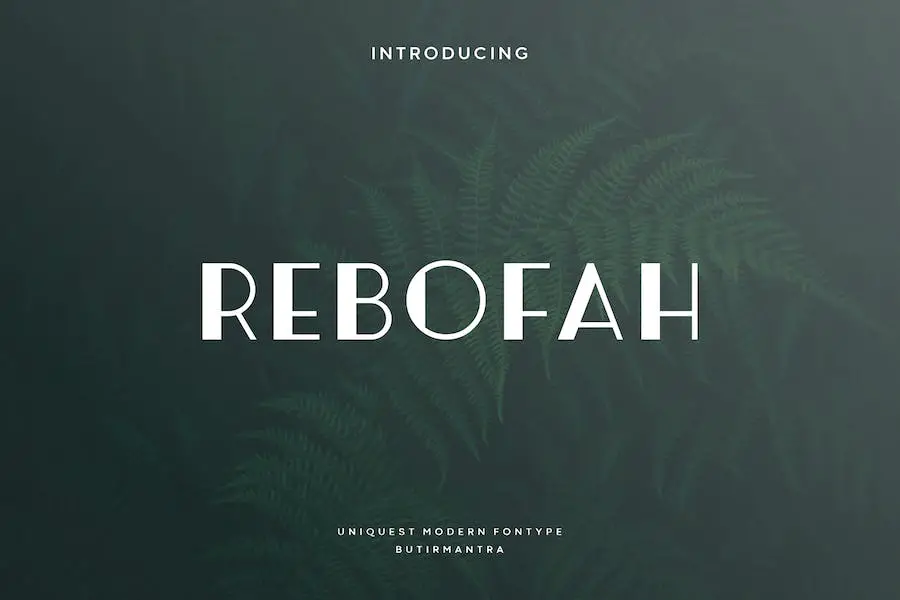
Rebofah는 독특한 스타일과 대문자에 약간의 트위스트를 제공하는 디스플레이 글꼴입니다. 음식, 일러스트레이션, 책 제목, 웹사이트 머리글, 비디오 작성 및 기타 그래픽 디자인 요구 사항과 관련된 프로젝트에 완벽한 선택입니다.
눈길을 끄는 모양과 다양한 기능을 갖춘 Rebofah는 디자인을 향상시키고 창의성을 더할 것입니다.
애니스톤
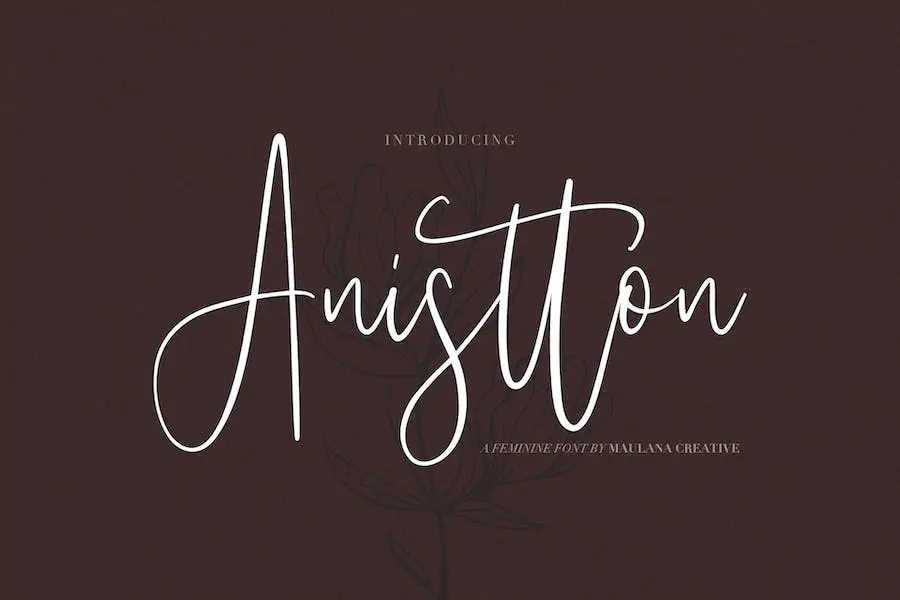
Anistton은 당신의 디자인에 정통 수공예 터치를 더해줄 글꼴입니다. 서명, 편지지, 로고, 타이포그래피 인용문 등에 적합합니다.
브러시와 같은 스타일로 잡지나 책 표지, 웹사이트 헤더, 전단지, 의류, 브랜딩, 패키징 등 다양한 디자인 프로젝트에 사용할 수 있는 다재다능한 애니스톤입니다.
소리녹 고우스
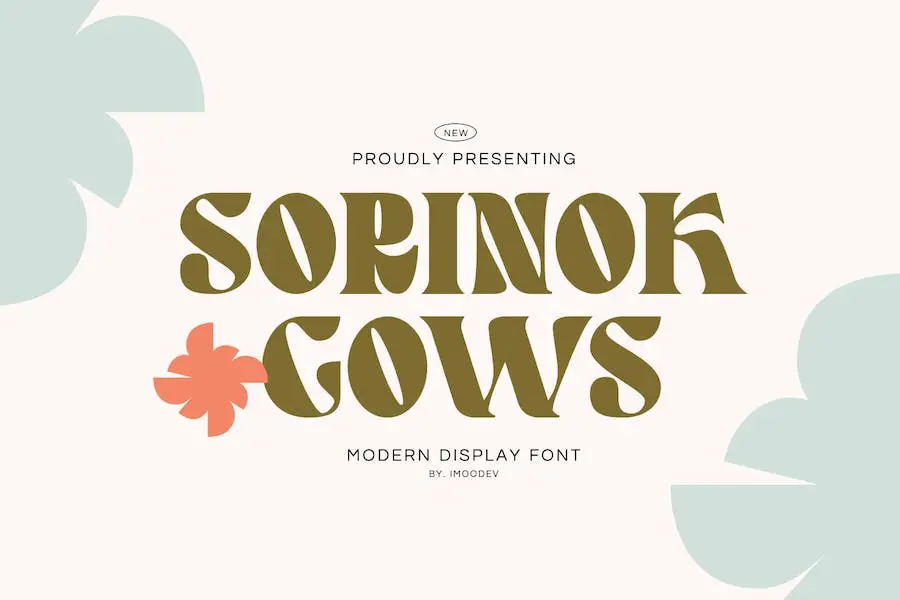
소리녹고우스는 크고 작은 사이즈 모두 사용이 가능한 다재다능한 폰트입니다. 개인 프로젝트부터 스튜디오, 기업체, 크리에이티브 에이전시, 산업체까지 다양한 비즈니스 분야에서 활용할 수 있습니다.
Opentype 기능과 다국어 지원을 통해 Sorinok Gows는 많은 유연성과 사용자 정의 옵션을 제공합니다. 구두점, 숫자, 기호, 대문자 및 소문자의 완전한 세트를 포함합니다.
스윗샤인
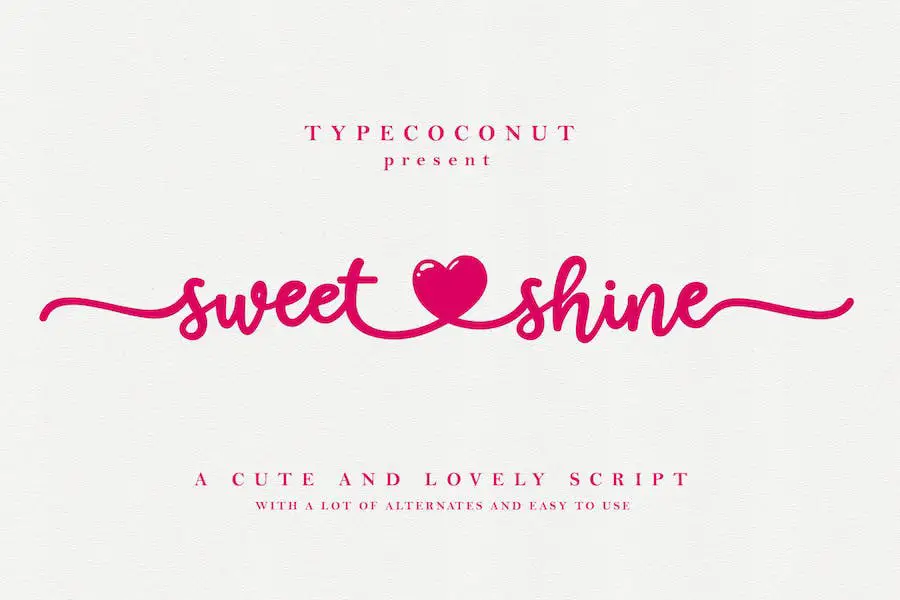
Sweet Shine은 다양한 프로젝트에 적합한 멋진 손글씨 스크립트 글꼴입니다. 공예 프로젝트, 웨딩 디자인 또는 현대적인 의류 작업을 하거나 눈길을 끄는 광고용 글꼴이 필요한 경우 이 글꼴이 이상적인 선택입니다.
아름답고 복잡한 레터링이 있는 Sweet Shine은 완벽한 구성을 만드는 데 도움이 되는 다양한 대체 스타일을 제공합니다. 손끝에서 개인 서예가를 갖는 것과 같습니다.
에사쿠
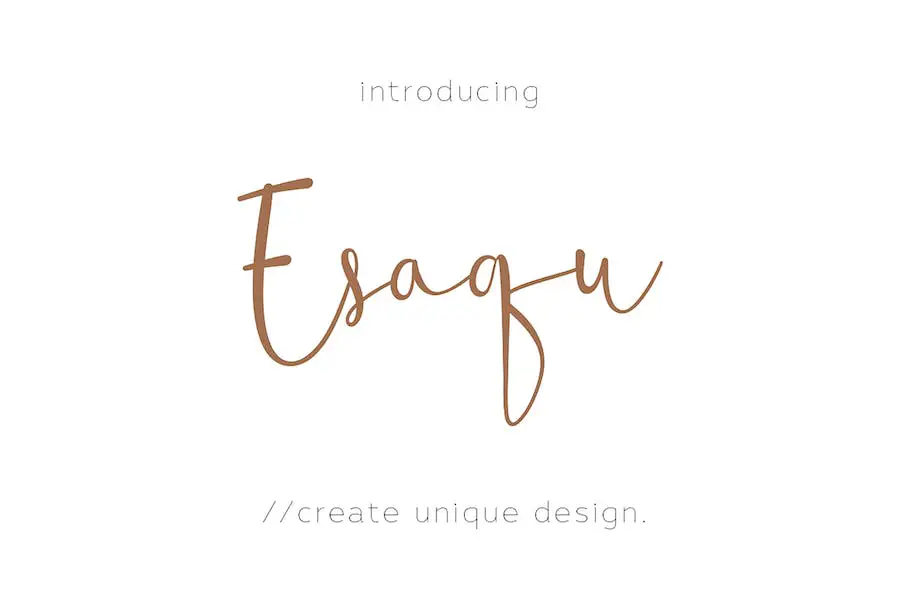
Esaqu는 디자인 프로젝트에 우아하고 독특한 터치를 더하는 세련되고 아름다운 여성스러운 글꼴입니다. 핸드 레터링 스타일로 어떤 디자인에도 자연스럽고 핸드메이드 느낌을 줍니다.
가느다란 선과 굵은 선의 조합과 깨끗한 스크래치가 어우러져 아름답고 시각적으로 매력적인 모습을 연출합니다.
브랜딩에 여성스러운 터치를 추가하고 싶거나, 멋진 청첩장을 만들거나, 눈길을 끄는 배너를 디자인하거나, 아름다운 로고와 레터링을 만들고 싶다면 Esaqu가 완벽한 선택입니다.
싱클레어
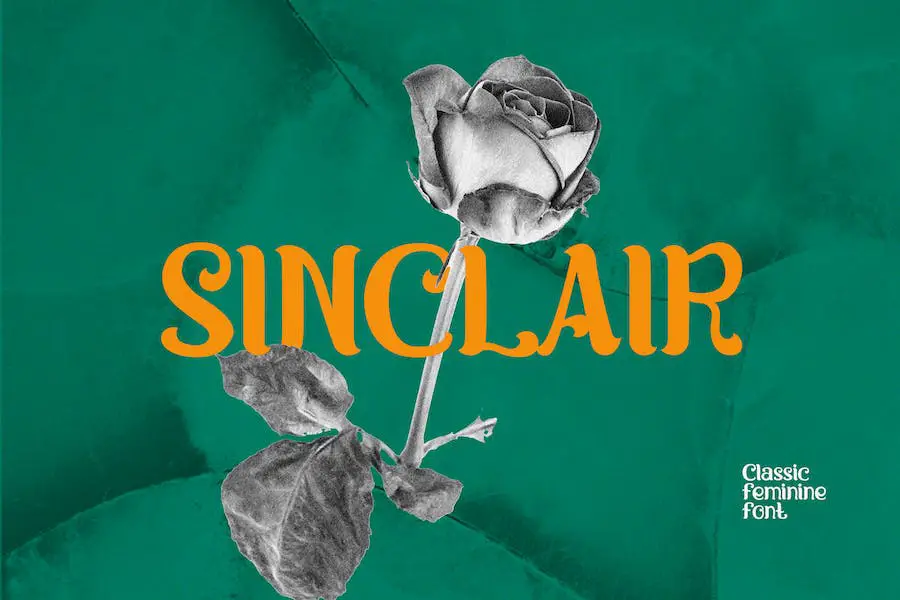
SINCLAIR는 모든 프로젝트에 화려한 스타일을 제공하는 우아한 여성스러운 느낌의 세리프 글꼴입니다. 세련되고 아름다운 디자인으로 디자인에 세련미를 더하는 데 적합합니다.
다양한 응용 분야에 적합한 SINCLAIR는 책, 여성스러운 포스터, 문구류, 학용품 글꼴, YouTube 표지, YouTube 섬네일, 소셜 미디어 페이지 표지 등에서 성숙하고 우아한 테마를 만드는 데 이상적인 다용도 글꼴입니다.
카말라
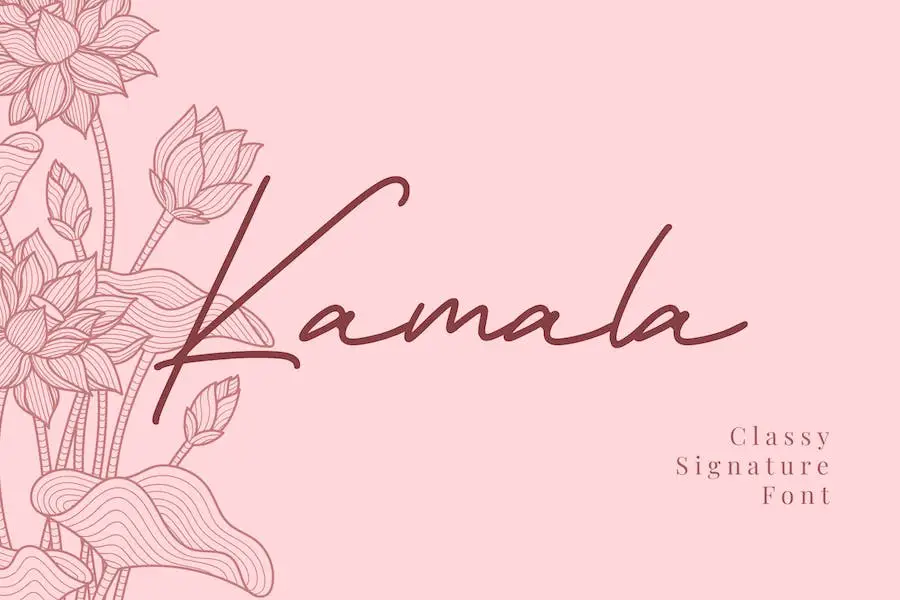
Kamala는 우아함과 다재다능함을 발산하는 시그니처 스크립트 글꼴입니다. 부드럽고 자연스러운 선이 있는 이 글꼴은 이름, 로고 또는 모든 디자인 프로젝트에 고급스러운 느낌을 더하는 데 적합합니다.
멋진 서명과 세련된 로고를 만들고 보석 및 유기농 식품 포장의 아름다움을 향상시키는 데 특히 이상적입니다. 또한 Kamala는 모든 로맨틱한 이벤트에 세련미를 더하기 때문에 청첩장을 위한 훌륭한 선택입니다.
안테미아
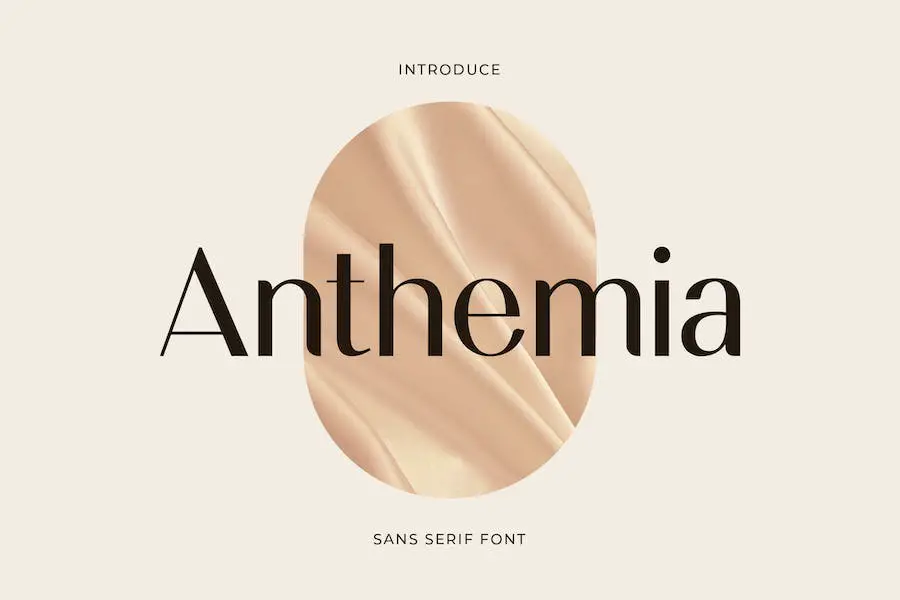
Anthemia는 프로젝트에 아름다움, 품격, 우아함을 더하기 위해 디자인된 멋진 여성스러운 세리프 글꼴입니다. 로고, 청첩장, 잡지 표지 또는 웹사이트 헤더 작업에 관계없이 이 글꼴은 모든 창의적인 노력에 완벽하게 적합합니다.
현대적이고 세련된 미학으로 다양한 스타일과 테마에 맞출 수 있을 만큼 다재다능합니다.
또한 여성적 특성과 남성적 특성을 자연스럽게 혼합하여 패션 관련 브랜딩 또는 편집 디자인에 탁월한 선택입니다. 귀하의 디자인에 우아함과 스타일을 더해줄 Anthemia만 있으면 됩니다.
뒤죽박죽 인
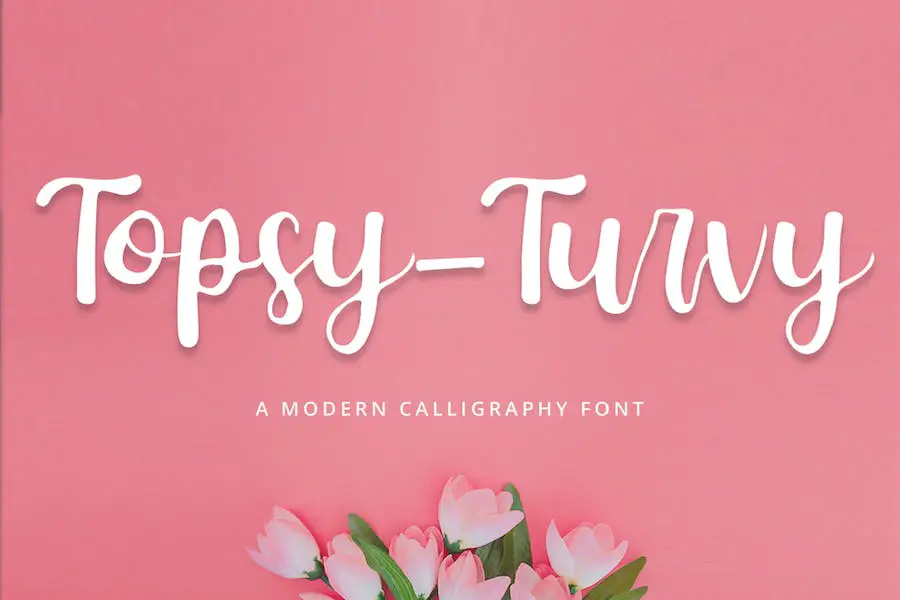
청중, 클라이언트 또는 손님을 사로잡을 재미있고 다양한 글꼴인 Topsy-Turvy를 소개합니다. 구두점과 숫자가 모두 포함된 이 현대적인 캘리그라피 글꼴은 프로젝트에 우아함을 더하는 데 적합합니다.
제목/제목과 본문 카피 사이에 완벽한 대조를 만들고 싶습니까? Topsy-Turvy가 답입니다. 뷰티 인플루언서, 인테리어 디자이너, 요리 유튜브 채널을 운영하는 등 다양한 콘텐츠 니즈와 프로젝트에 활용할 수 있는 폰트입니다.
사비아나
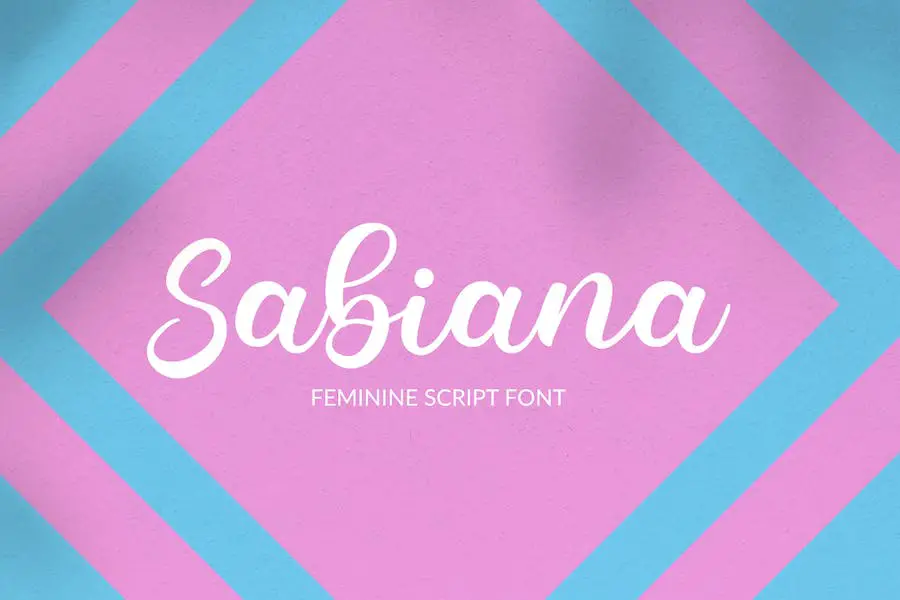
이 TTF 글꼴은 아름다운 브랜딩 프로젝트, 패셔너블한 잡지 레이아웃, 시선을 사로잡는 포장 디자인, 시선을 사로잡는 소셜 미디어 게시물을 만드는 데 적합합니다. 또한 청첩장 및 연하장을 위한 탁월한 선택입니다.
Sabiana의 뛰어난 기능 중 하나는 다양한 언어를 지원하여 광범위한 사용자가 액세스할 수 있다는 것입니다. 다른 언어로 디자인을 만들거나 국제 청중을 수용해야 하는 경우 이 글꼴을 사용할 수 있습니다.
발레인
Ballein의 눈에 띄는 기능 중 하나는 광범위한 대체 대문자 세트입니다. 즉, 선택할 수 있는 옵션이 매우 다양하여 프로젝트에 가장 적합한 것을 찾을 수 있습니다.
뿐만 아니라 Ballein은 합자를 여러 글꼴로 선택하여 훨씬 더 다재다능하고 창의적인 자유를 제공합니다.
가리
여성스러움을 더해 프로젝트를 향상시킬 수 있는 이상적인 글꼴을 찾고 있는 그래픽 디자이너라면 Girly가 적합합니다. 이 글꼴은 세련되고 매력적인 글꼴을 찾는 현대 디자이너의 요구를 충족시키기 위해 특별히 제작되었습니다.
우아하고 고급스러운 디자인으로 Girly는 시장에서 가장 좋아하는 제품이 될 것입니다. Girly의 주요 기능 중 하나는 다양성입니다.
이 세리프체는 표준 대문자와 소문자를 제공할 뿐만 아니라 대문자에 대한 다양한 대체 문체도 제공합니다. 이를 통해 디자인에 대한 완벽한 모양을 실험하고 선택할 수 있습니다.
우화
Allegory는 불완전한 터치와 깔끔한 마무리가 결합된 소녀스러운 스크립트 글꼴로 어떤 프로젝트에도 적합합니다. 숫자와 구두점을 사용하여 따옴표, 인사말 카드, 청첩장 또는 여성스럽고 현대적인 모든 것을 만드는 데 이상적입니다.
또한 Allegory에는 장식품이 포함된 두 번째 글꼴이 함께 제공되어 디자인에 달콤한 느낌을 더할 수 있습니다. 이 글꼴은 대문자와 소문자를 모두 지원하며 언어 지원을 제공합니다.
전반적으로 Allegory는 프로젝트 디자인을 향상시키는 다재다능하고 매력적인 글꼴입니다.
결론
요약하자면, 이 기사에서는 그래픽 디자인 프로젝트를 다음 단계로 끌어올릴 수 있는 최고의 여성스러운 글꼴에 대해 논의했습니다. 우아하고 섬세한 스크립트 글꼴에서 대담하고 자신감 있는 디스플레이 글꼴에 이르기까지 모든 프로젝트와 스타일에 맞는 무언가가 있습니다.